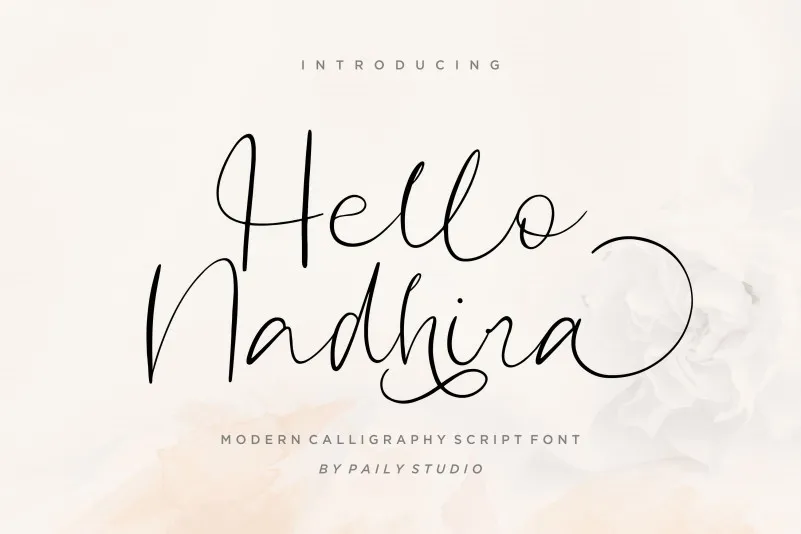
Hello Nadhira Calligraphy Font – Download Grátis
Esta é uma fonte de escrita moderna que proporciona opções únicas para diversos projetos visuais. A fonte “Hello Nadhira” é perfeitamente adaptada para um amplo range de aplicativos, incluindo designs para casamentos, iniciativas de marca, logotipos, materiais publicitários, cartões de nome, convites e postagens nas redes sociais. Com seu charme elegante e moderno, a fonte “Hello Nadhira” oferece uma maneira criativa de personalizar seus projetos. Seja você designer gráfico ou profissional de design, a escolha desta fonte adicionará um toque especial ao seu trabalho, tornando-o mais único e envolvente. O Designer Paily Studio lançou esta fonte de escrita moderna com estilo, destinada a ajudar designers de todo o mundo a expressarem suas ideias de maneira única. A fonte “Hello Nadhira” é uma escolha inteligente para quem quer dar vida a seus projetos visuais, tornando cada trabalho mais especial e personalizado.